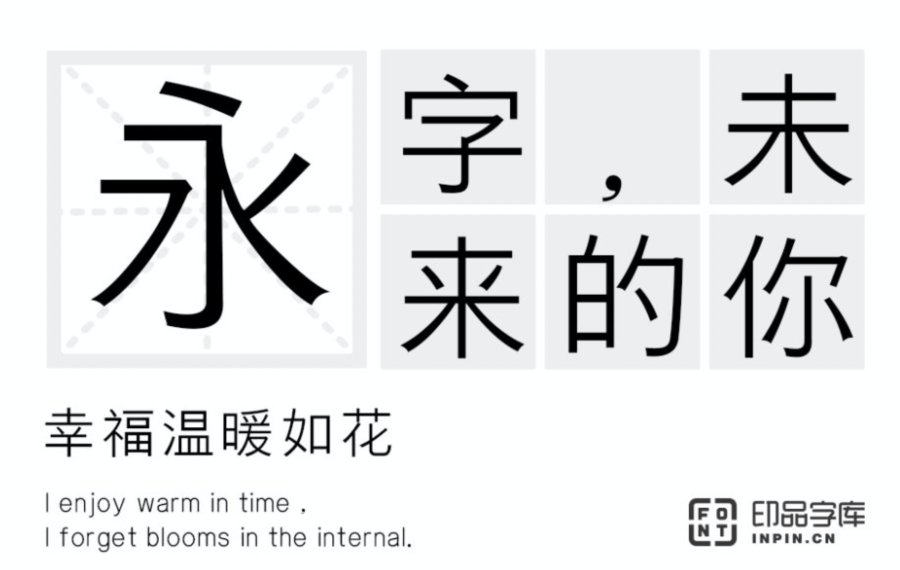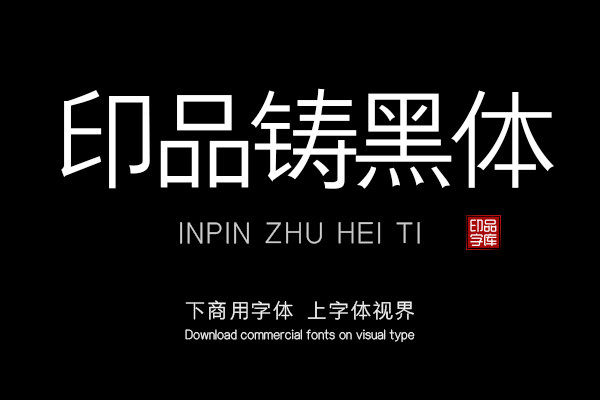
印品铸黑体出自印品字库,耗时2年于2019年发布上市。是一款为电脑系统打造的字体。
印品铸黑体折笔处采用了书法中的顿笔的笔法,笔画呈起笔点细,落笔粗的微喇叭口状,流畅弧线,延续了传统字体的笔法。这款字体整体重心略偏下,中宮稍紧,字面稍小,结构明朗清晰,易于阅读且有较好的辨识度和视觉效果。印品铸黑体整体呈现出清秀俊美,笔画简洁明快,有较好的的阅读感。这是一款完胜系统风的黑体,可用于标题、正文、LOGO、广告、印刷、屏显、印章等场景。